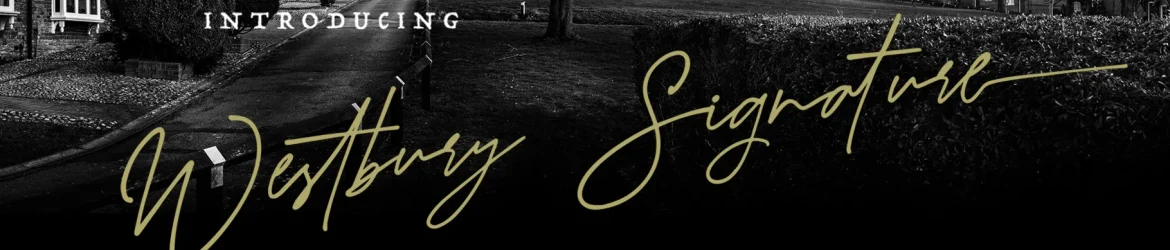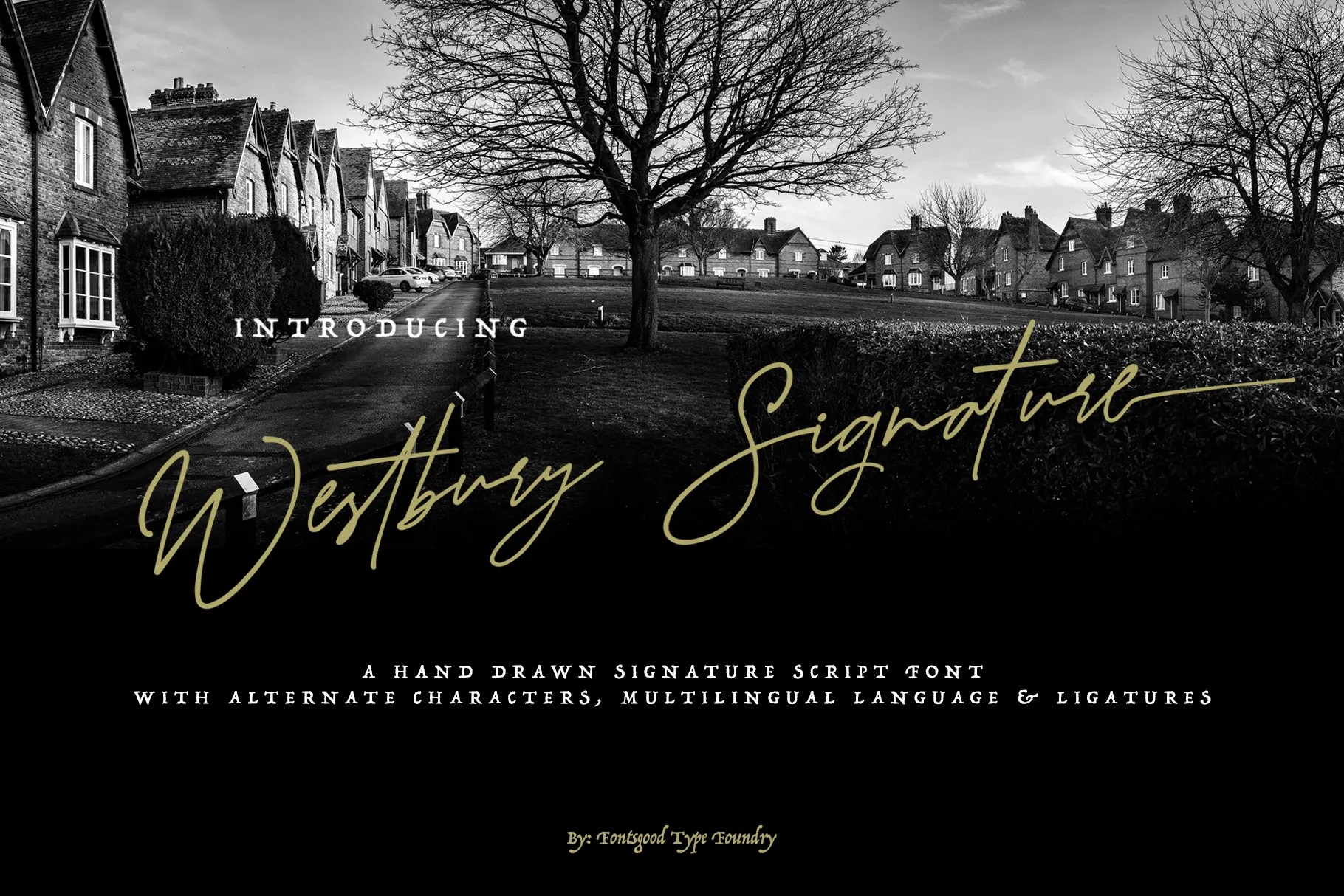
Westbury Signature Demo Font – Fonte Grátis
Westbury Signature Demo Font
Introduzimos a fonte de escrita “Westbury Signature”, criada para aqueles que buscam uma pitada elegante e única, combinando o estilo manual com a modernidade para seus projetos. Se você precisa de uma adição sofisticada para suas criações digitais, essa é a fonte perfeita. Através da mão-dura do artista tipógrafo que criou “Westbury Signature”, você pode personalizar os assinaturas e logotipos com um ar delicado sem perder o toque moderno. Esta font foi desenvolvida para aqueles que valorizam tanto a elegância quanto a simplicidade, oferecendo uma opção realista e única para quem busca expressar seu estilo em seus projetos digitais. Com “Westbury Signature”, suas criações ganharão um toque autêntico de arte manual.
Designer: Fontsgood